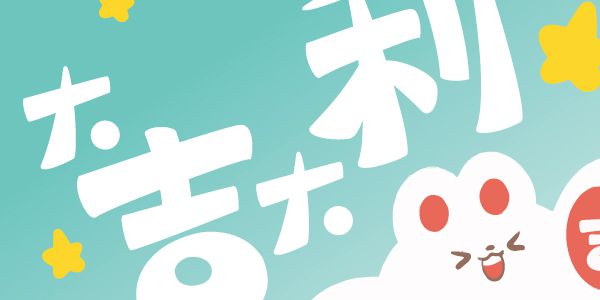
一款浓墨重彩的书写体
汉仪尚巍墨白是由汉仪字库签约作者尚巍创作的一款极具视觉形式感的个性书写字体,变化丰富的字形轮廓与粗密简省的笔画造型构成了独特的书写风格,融合了朴拙的书写与现代审美趣味。
这款字体适合用于标题字体的排版,版面整体效果呈现出错落有致的书写节奏感;或用于装饰性的排版,例如放大单个字,视觉冲击力强且细节丰富。在书籍封面、海报广告、产品包装等应用场景中可以抓人眼球,令人印象深刻,营造悠闲舒适、愉快惬意的气氛。
字形轮廓以方形为基础,依汉字结构的不同以及构成笔画的多少而有丰富变化,或长或扁、或宽或窄,高低错落的书写节奏感。
字形变化丰富而夸张的同时保持平正与稳定。
等粗的笔画造型简省概括,平直笔画与弧形笔画结合,方圆并济。
书写笔触自然形成的飞白和不规则的边缘为粗密的笔画增添了空气感。
汉仪尚巍墨白的西文部分由汉仪字库西文字体设计师史贺达创作,保持与中文部分一致的书写风格,由等粗的几何笔画构成方整的字形,保留自然的书写笔触。
汉仪尚巍墨白以造型轮廓的规整简洁中和了字形笔画的夸张,使得这款字体在排版应用中形成了独特视觉形式感的同时保证了文本内容的易读性。这款字体个性的书写节奏感让排版轻快明朗起来。